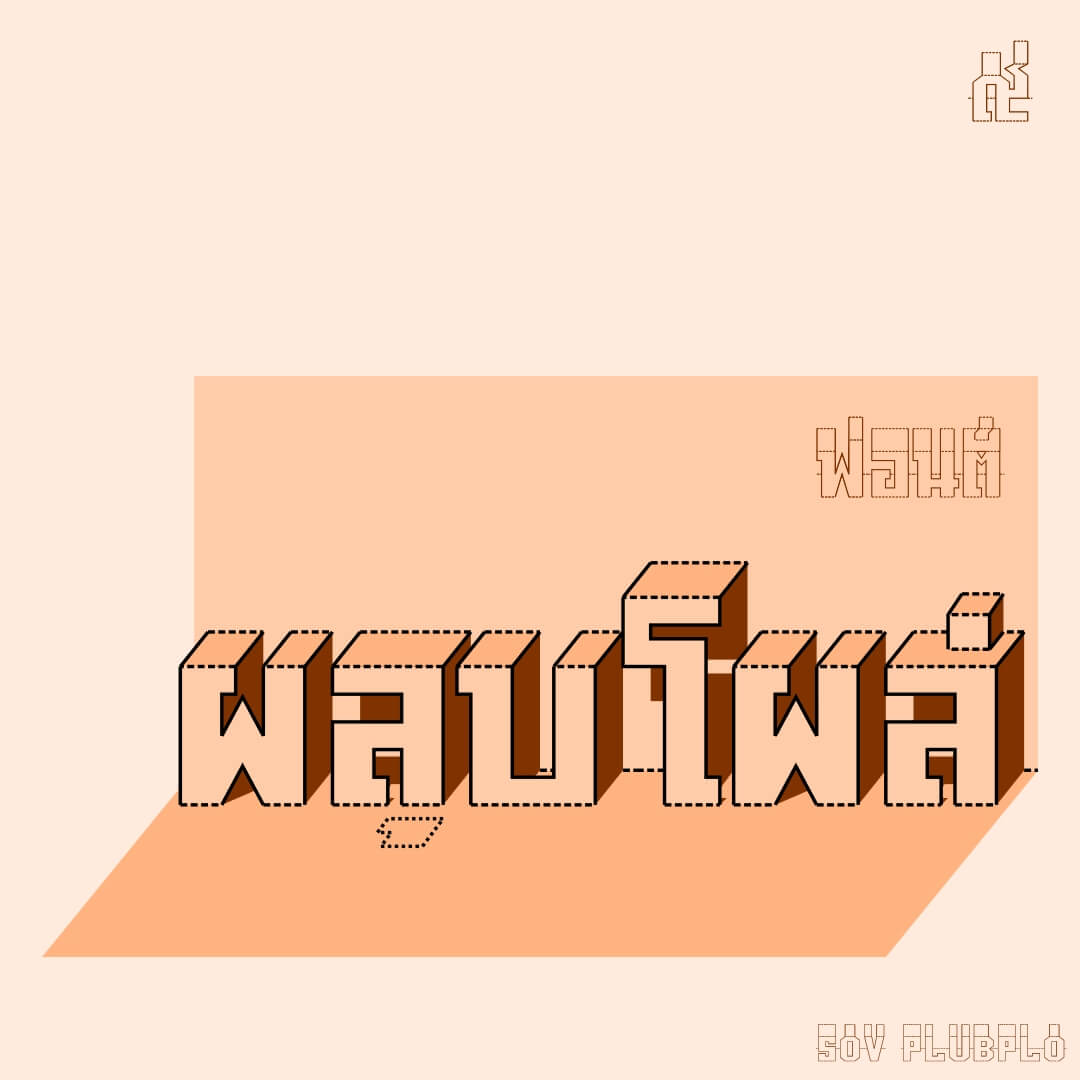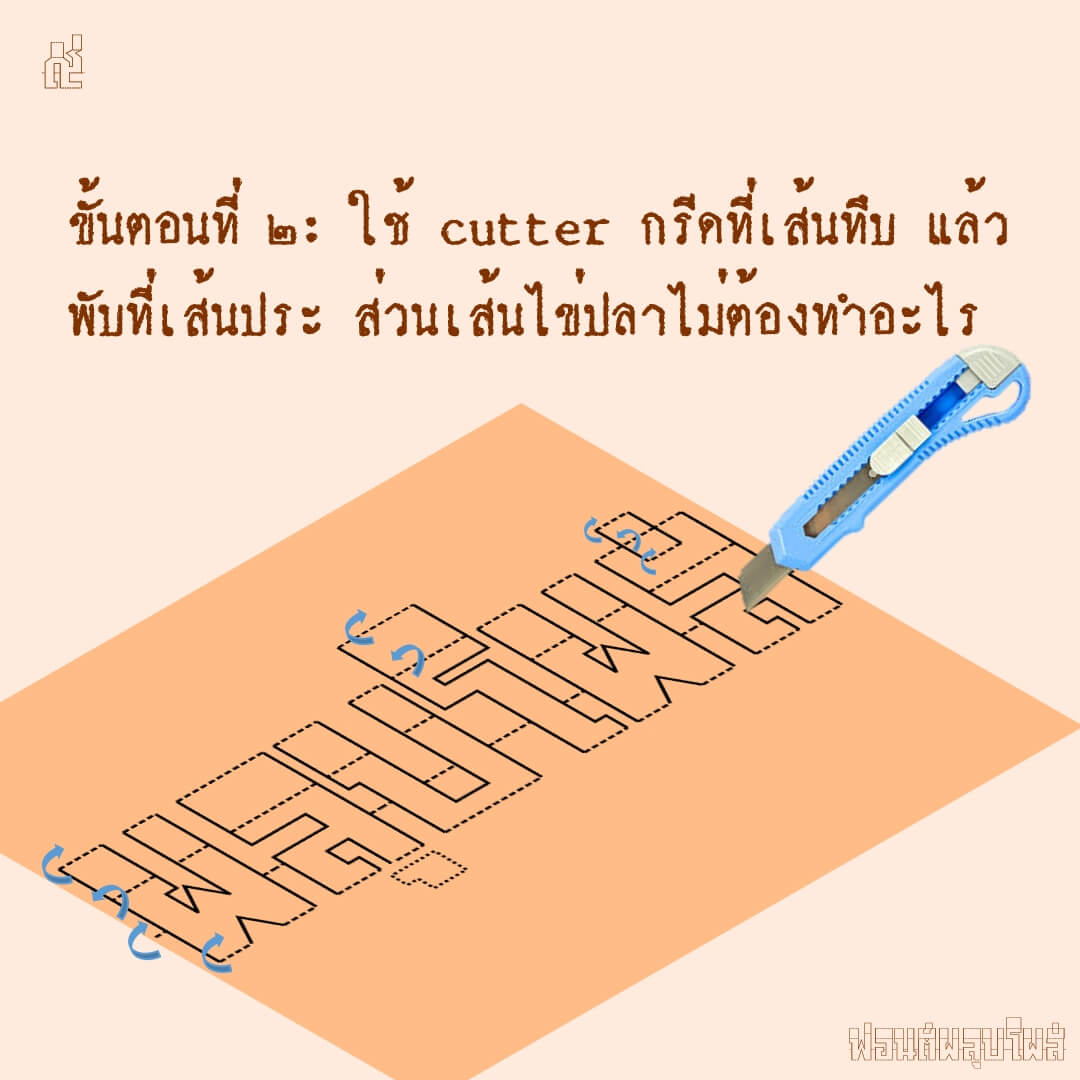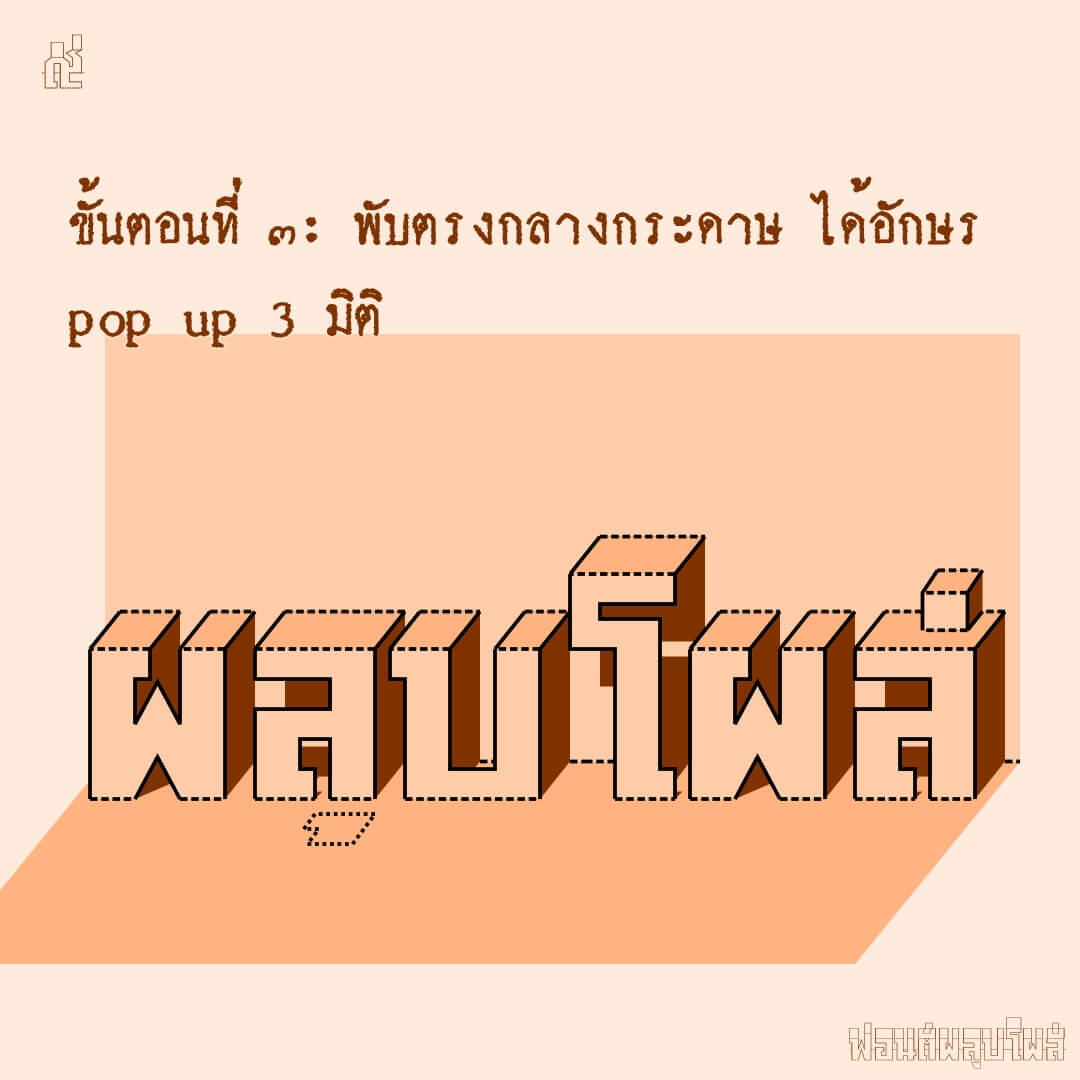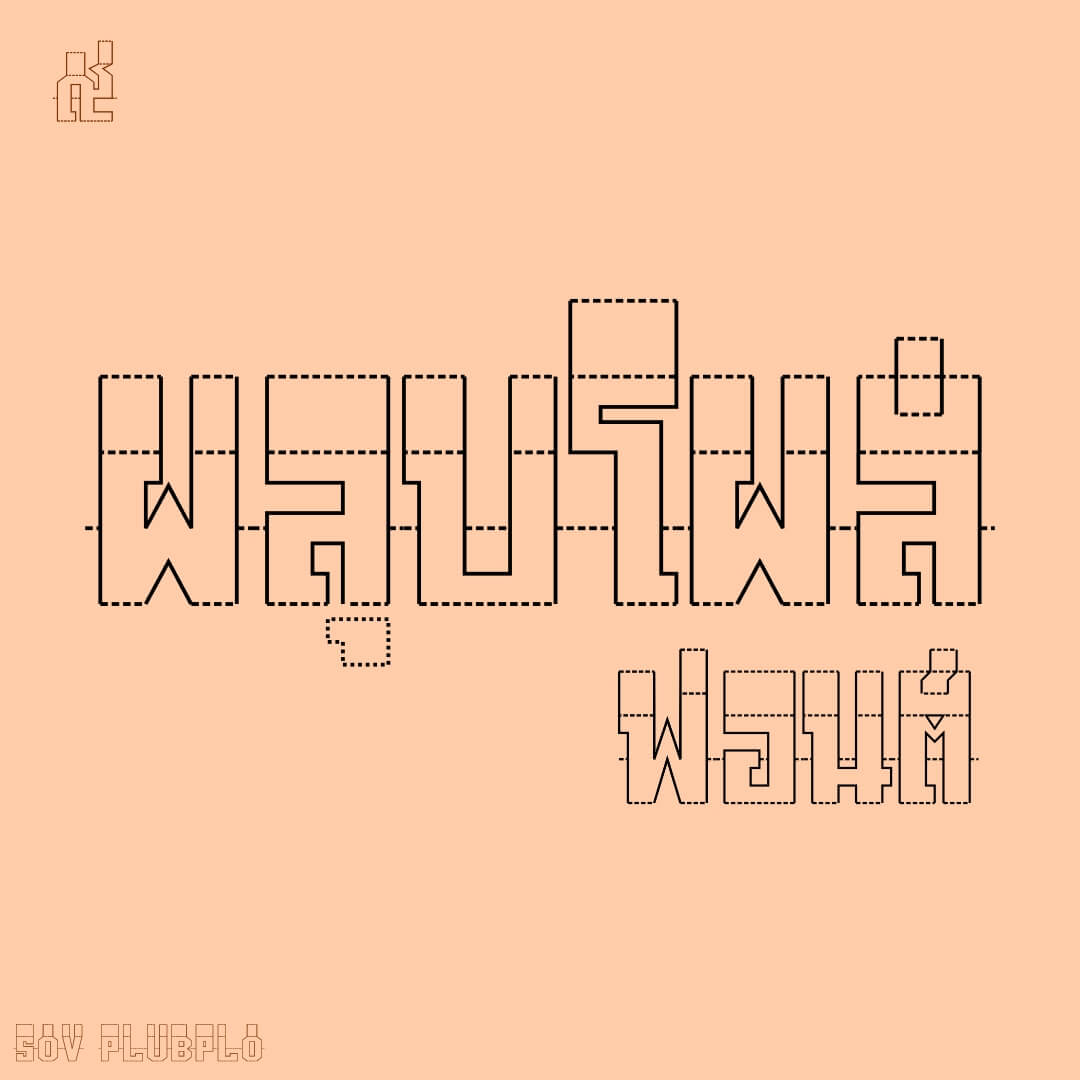
ฟอนต์ผลุบโผล่ – เป็นเส้นอักษรสำหรับทำตัวหนังสือ pop up 3 มิติ อักษรไทย เส้นทึบ…ให้ตัด เส้นประ…ให้พับ เส้นไข่ปลา… ไม่ต้องทำอะไร
เบื้องหลังการออกแบบ : ฟอนต์ ผลุบโผล่
ผลุบโผล่ (SOV_PlubPlo)